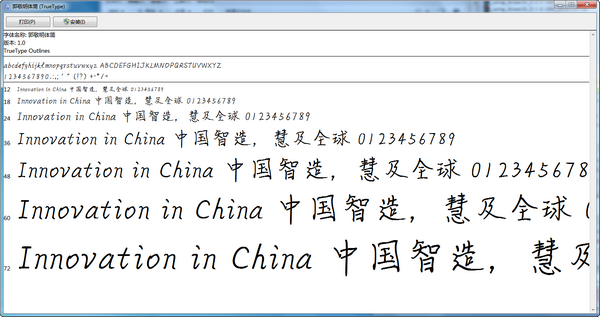
漢儀郭敬明體是作家郭敬明與漢儀字庫(kù)聯(lián)合打造的一款清新灑脫的簡(jiǎn)體中文字體,主要適用于手機(jī)qq中,有需要者歡迎直接下載!
2015年4月29日,由郭敬明親手書(shū)寫聯(lián)合漢儀字庫(kù)出品的字體,在手機(jī)qq個(gè)性裝扮聊天字體里首發(fā)。該字體清冽優(yōu)雅、從容灑脫,保持了郭敬明原汁原味的手寫體風(fēng)格,成為又一明星手寫體計(jì)算機(jī)字體。
漢儀郭敬明體專為手機(jī)聊天社交體驗(yàn)而打造,既適合廣大QQ網(wǎng)友和郭敬明的粉絲使用,也是所有手寫字體愛(ài)好者的全新選擇。
漢儀郭敬明體還額外增加了包括“囧”等300個(gè)互聯(lián)網(wǎng)常用字,使這款字體在完美表現(xiàn)郭敬明寫字風(fēng)格的同時(shí),成為一款真正意義上的計(jì)算機(jī)字庫(kù)產(chǎn)品。
漢儀郭敬明體整體風(fēng)格簡(jiǎn)約優(yōu)雅、清新灑脫,筆畫清晰而隨意,非常有個(gè)性易于辨識(shí)。